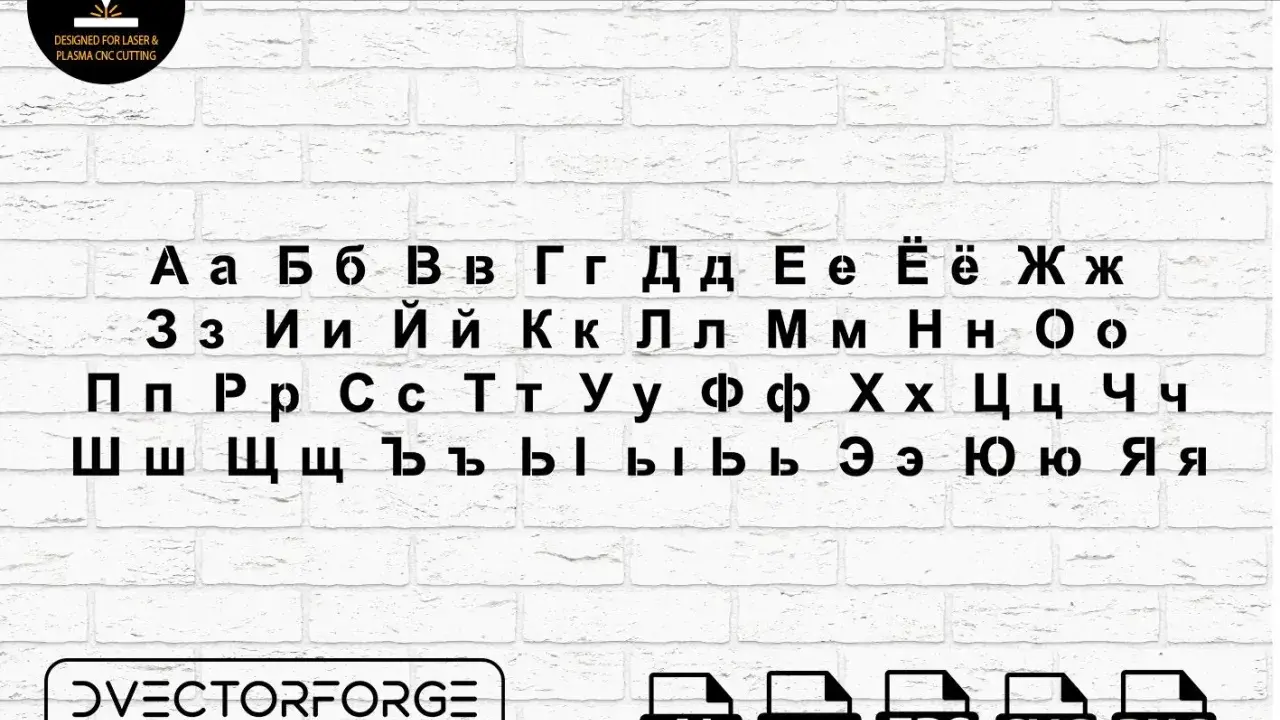
Czcionka cyrylica - Wybierz dobrze, uniknij błędów!
Cyrylica w wersji szablonowej, idealna do cięcia laserem i plazmą. Zestaw liter alfabetu cyrylica.
W projektach brandingowych i webowych cyrylica nie jest dodatkiem, który można dorzucić na końcu. W praktyce czcionka cyrylica to po prostu font z pełnym zestawem znaków cyrylickich, ale w dobrym projekcie liczy się też rytm liter, kursywa, pogrubienie i zgodność z językiem, w którym tekst ma żyć. Poniżej pokazuję, jak odróżnić solidny krój od przypadkowego wyboru, które style typograficzne najczęściej działają najlepiej i jak wdrożyć je bez typowych błędów.
Najważniejsze rzeczy do sprawdzenia przed wyborem fontu
• Sprawdź nie tylko obecność cyrylicy, ale też komplet znaków, kursywę i pogrubienie.
• Porównaj litery podobne do łacińskich, bo to one najczęściej zdradzają słaby projekt.
• Jeśli projekt trafia na różne rynki słowiańskie, zweryfikuj lokalne formy znaków w OpenType.
• Do UI i długich tekstów zwykle najlepiej działają proste groteski i klasyczne szeryfy, a nie ozdobne displaye.
• W webie ładuj tylko potrzebne wagi i subsety, bo to wyraźnie wpływa na szybkość strony.
Co naprawdę oznacza font z cyrylicą
Font z obsługą cyrylicy nie jest zwykłą kopią łacińskiego kroju z doklejonymi znakami. To zestaw glifów, który musi działać spójnie w kilku alfabetach jednocześnie, a więc zachować podobny kontrast, ciężar, szerokość i charakter kreski. Jeśli ten balans się rozjeżdża, tekst wygląda jak złożony z dwóch różnych rodzin, nawet gdy technicznie wszystko się zgadza.
Ja patrzę na to przede wszystkim przez pryzmat zastosowania. W identyfikacji marki ważna jest osobowość, ale w artykule, aplikacji albo systemie interfejsów ważniejsza bywa czytelność i stabilny rytm. Warto też pamiętać, że samo „ma cyrylicę” nie oznacza jeszcze, że font ma komplet wag, kursywę i poprawne formy lokalne. To właśnie te detale decydują, czy krój naprawdę nadaje się do pracy, czy tylko dobrze wygląda na pojedynczym podglądzie. Skoro to już jasne, można przejść do praktycznego sprawdzania fontu przed wdrożeniem.
Jak rozpoznać dobry font z cyrylicą przed publikacją
Ja zawsze testuję font w takich samych warunkach, w jakich ma potem pracować. Pojedyncza litera na białym tle niewiele mówi, bo dopiero dłuższy ciąg znaków pokazuje, czy odstępy, grubość i kształty są naprawdę dopracowane. Jeśli projekt ma trafić do druku, na stronę i do materiałów social media, test powinien obejmować wszystkie te konteksty.
Co sprawdzić Dlaczego to ważne Jak to przetestować
Zakres znaków Brak jednej litery potrafi zepsuć cały skład Wpisz kilka słów z różnymi znakami cyrylickimi, nie tylko jedno hasło
Kursywa i pogrubienie Bez pełnej rodziny font nie działa jak system Porównaj regular, italic i bold obok siebie
Kerning Złe odstępy widać natychmiast, szczególnie w nagłówkach Sprawdź krótkie tytuły i dłuższe frazy w kilku rozmiarach
Formy lokalne W niektórych językach cyrylickich obowiązują inne warianty liter Zweryfikuj feature locl i dokumentację rodziny
W testach używam nie tylko podstawowych liter, ale też znaków, które często ujawniają słabe dopracowanie: Ж, Я, Ы, Ю, Д, Л. Jeśli któraś z nich wygląda jak obca w ciele fontu, zwykle nie ma sensu liczyć na cud w większym projekcie. Przy szerokim pokryciu znaków dobrym punktem startu bywa też Noto, które Google Fonts opisuje jako kolekcję obejmującą ponad 1000 języków i ponad 150 systemów pisma. To nie znaczy, że zawsze trzeba sięgać po najcięższą armatę, ale jako baza bezpieczeństwa taki wybór ma sens. Po tej kontroli łatwiej zdecydować, jaki styl pisma będzie faktycznie działał w projekcie.
Które style typograficzne najczęściej wygrywają w praktyce
W bibliotekach takich jak Google Fonts można znaleźć wiele rodzin z cyrylicą, ale sama dostępność niczego jeszcze nie rozwiązuje. Styl pisma powinien pasować do zadania, a nie tylko do gustu projektanta. Ja zwykle rozdzielam wybór na trzy sytuacje: tekst użytkowy, treści redakcyjne i akcent wizualny. Każda z nich ma trochę inne wymagania.
Styl Kiedy działa najlepiej Przykłady rodzin Na co uważać
Sans serif UI, strony firmowe, oznakowanie Noto Sans, Montserrat Musi mieć dobry rytm w małych rozmiarach
Serif Artykuły, publikacje, marki premium PT Serif, Merriweather Kursywa i kontrast muszą być dopracowane
Display Logo, nagłówki, kampanie Russo One, Unbounded Łatwo przeładować layout, jeśli użyjesz ich zbyt dużo
Najczęściej wygrywa prosty podział: do długiego tekstu wybieram spokój, do nagłówka charakter, a do logo tylko tyle ekspresji, ile da się utrzymać w obu alfabetach. Jeśli pracuję nad marką, która ma komunikować nowoczesność, bezszeryfowa rodzina daje zwykle największą elastyczność. Gdy zależy mi na bardziej redakcyjnym, „wiarygodnym” wrażeniu, szeryf potrafi zrobić lepszą robotę, o ile nie traci czytelności w mniejszych stopniach. To prowadzi prosto do kolejnego pytania: jak taki font wdrożyć, żeby nie spowolnić strony i nie zrobić bałaganu w plikach.